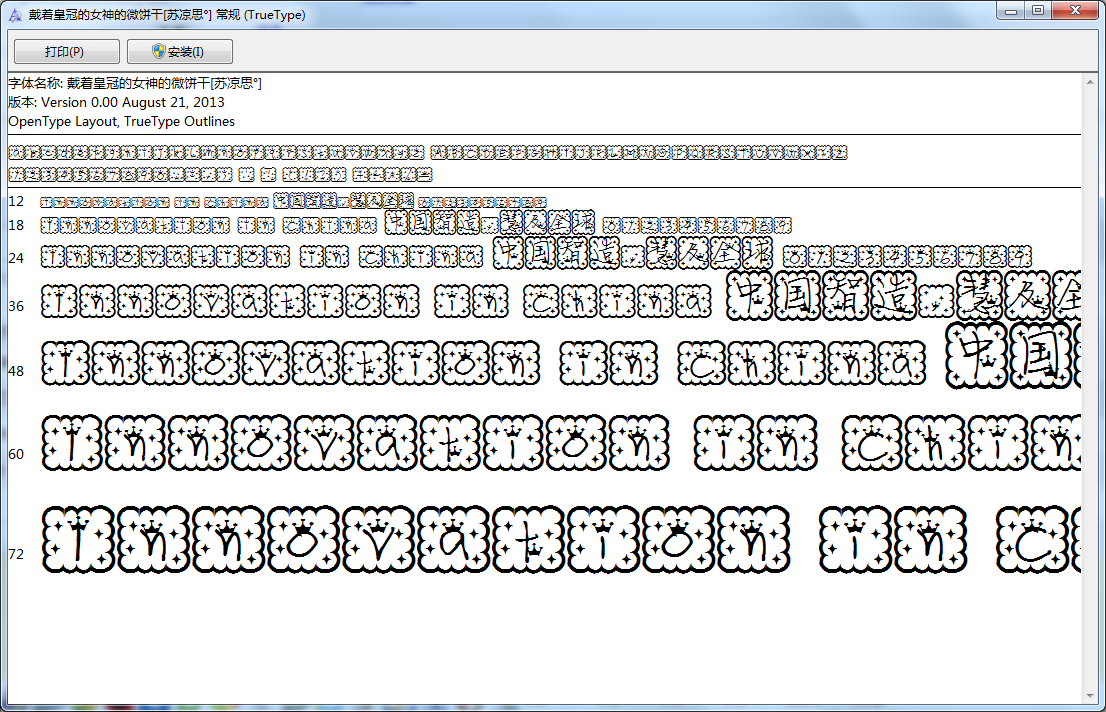
女神的微餅干字體
女神的微餅干字體是一款非常漂亮可愛的字體,字體的外面有一圈圓形的卡通圖案,還有星星做點(diǎn)綴,非常適合女生使用,喜愛的朋友趕快下載體驗吧!
字體的周邊加入了一些餅干圖形卡通圖案,非常具有創(chuàng)意,能夠適用于圖形圖像設(shè)計、電腦切割、動畫創(chuàng)作、工程制圖、高精度專業(yè)等行業(yè)。